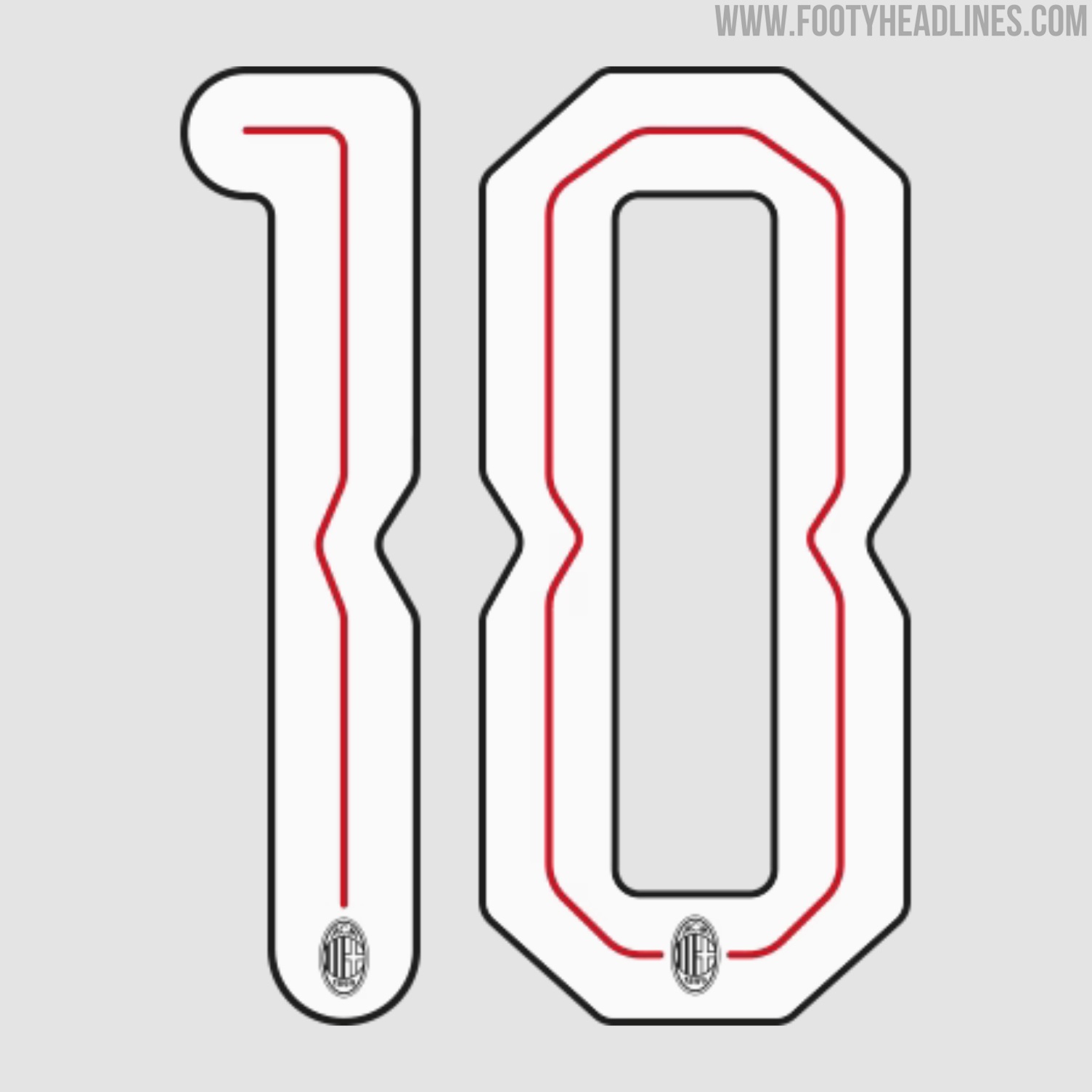
Rilasciato il nuovo font della maglia AC Milan 24-25
- Nuovo font della maglia dell'AC Milan: L'AC Milan ha rilasciato il nuovo font della maglia 24-25, che sarà utilizzato per la Champions League e la Coppa dei Campioni.
- Design del font: Il nuovo font della maglia del Milan 24-25 presenta un design interessante con una combinazione di linee morbide e dure e tratti più sottili rispetto alla stagione precedente.
Il Milan ha lanciato la nuova maglia 24-25 che verrà utilizzata per la Champions League e la Coppa dei Campioni.
Il nuovo carattere della maglia del Milan 24-25
La nuova maglia di caratteri Milan 24-25 ha un design interessante con una combinazione di linee morbide e dure.
Il carattere A.C. Milan 24-25 presenta tratti più sottili rispetto alla stagione 23-24.